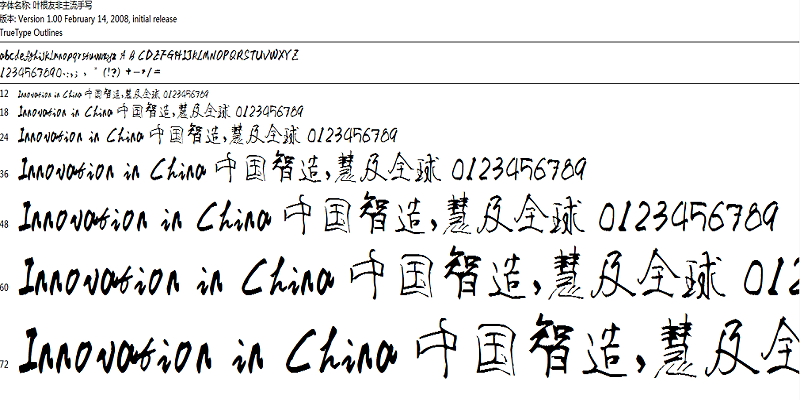
軟件介紹 軟件標簽: 葉根友字體 葉根友非主流手寫體是根據(jù)現(xiàn)在這個非主流體流行的時代應(yīng)運而生的書法字體,字體極具風格特色,不隨波逐流,確有積分非主流的特色,感興趣的朋友們快來下載吧!字體介紹:葉根友非主流鋼筆手寫體是由中國書法奇人葉根友先生書寫,字體清晰自然,實用性強,是書寫信件,BLOG等個性化字體的一不錯的選擇.相關(guān)推薦:葉根友仿劉德華字體 免費版授權(quán):免費軟件 WinAll大?。?.3M語言:中文葉根友仿劉德華字體是一款劉德華先生字體的仿版,字體表現(xiàn)十分自然,又極顯逼真,如果有劉德華先生的粉絲,一定不要錯過這款字體哦,趕快來綠色資源網(wǎng)下載體驗吧!字體介紹:劉德華字體葉根友仿版是由中國書法奇人葉下載地址安裝說明:如果您是Win7用戶直接右鍵選擇安裝即可,其他系統(tǒng)的用戶可以將字體文件復(fù)制到C:\Windows\Fonts文件夾即可完成安裝 軟件截圖 上一張下一張(1 / 1) 安裝詳細截圖 猜你喜歡 手寫體 葉根友 手寫體 手寫體又名手寫字體,是專門用手工書寫出來的字體。該類字體的筆畫一般比較細,不會很粗,給人一種細膩感;當然,也有中粗的手寫字體。喜歡的朋友,可以下載用用看。 查看更多>> 日系手寫字體 7.25M/中文/10.0/下載 偏偏情書手寫體 10.46M/中文/3.3/下載 悄悄話手寫體 8.34M/中文/0.0/下載 默陌肥圓手寫體字體 3.36M/中文/10.0/下載 默陌信箋手寫體字體 3.36M/中文/8.0/ttf免費版下載 南構(gòu)村花手寫體ttf版 2.22M/中文/0.3/下載 葉根友 葉根友字體是現(xiàn)代社會中使用最為廣泛的字體,包含葉根友疾風草書、葉根友刀鋒黑草等,現(xiàn)綠色資源網(wǎng)小編整合幾款葉根友字體大全供用戶下載,歡迎到綠色資源網(wǎng)體驗! 查看更多>> 葉根友哲在手寫字體 4.00M/中文/6.0/官方版下載 葉根友離賢行書字體 10.00M/中文/5.7/免費版下載 南構(gòu)字體合集 50.00M/中文/3.7/共16款下載 南構(gòu)汪本友行書字體 10.00M/中文/3.3/下載 南構(gòu)標羽歌士體 10.00M/中文/5.0/免費版下載 南構(gòu)王天喜行書簡體字體 10.00M/中文/2.1/下載 其他版本下載 標題 大小 更新日期 下載 下載地址 電腦版 葉根友非主流手寫體 免費版 點擊報錯 軟件無法下載或下載后無法使用,請點擊報錯,謝謝! 關(guān)閉報錯反饋 請描述您所遇到的錯誤,我們將盡快予以修正,謝謝! *必填項,請輸入內(nèi)容 本類最新 葉根友字體庫打包 共18款 葉根友風帆特色簡體 免費官方版 葉根友哲在手寫字體 官方版 南構(gòu)村花手寫體ttf版 南構(gòu)王小花手寫ttf常規(guī) 南構(gòu)日漫風字體 相關(guān)文章 主流服務(wù)器網(wǎng)卡Teaming模式配置 比僵尸更恐怖 五大主流僵尸網(wǎng)路全解析 用戶評論 熱門評論 最新評論 發(fā)表評論 查看所有評論(0) 昵稱: 請不要評論無意義或臟話,我們所有評論會有人工審核. 字數(shù): 0/500 (您的評論需要經(jīng)過審核才能顯示)